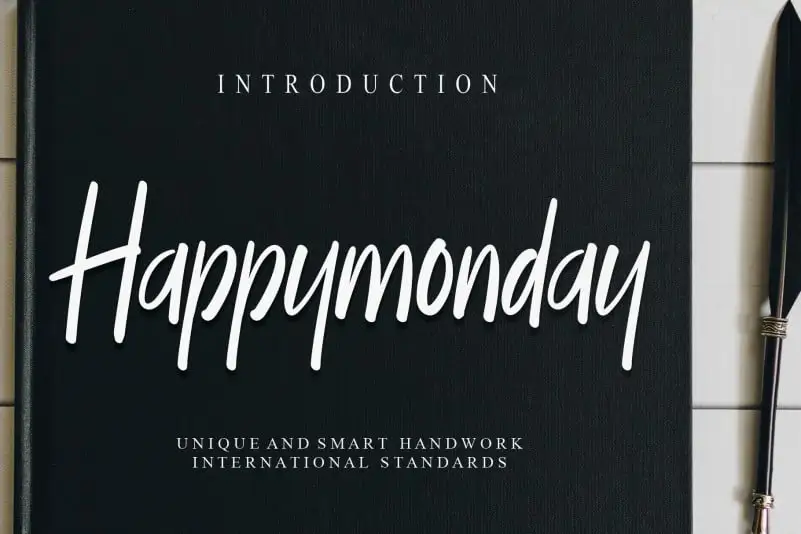
Happymonday Script Font – Download Grátis
A Happymonday Script Font é uma opção vibrante e delicada para quem busca adicionar um toque especial ao seu design. Seja você designer de logotipos, criador de materiais publicitários ou simplesmente alguém que quer dar um gás à sua escrita pessoal com algo de novo, esta fonte vai proporcionar uma experiência única. Adaptable e sofisticada, ela combina a elegância do estilo script com as sutilezas da estética moderna. Seja você um designer digital ou papel, esse tipo de letra trará vida ao seu projeto. A Happymonday Script é como um bom amigo que acompanha você em suas aventuras criativas, sempre pronto para fazer o seu trabalho sem deixar marcas indesejadas. Sua simplicidade é recompensada por uma qualidade de escrita profunda e sofisticada. Para designers mais atentos à atmosfera brasileira, essa fonte traz um ar quase familiar ao design digital, como se fosse um convite para explorar o universo criativo com a mesma leveza e alegria que define o nosso dia-a-dia no Brasil.